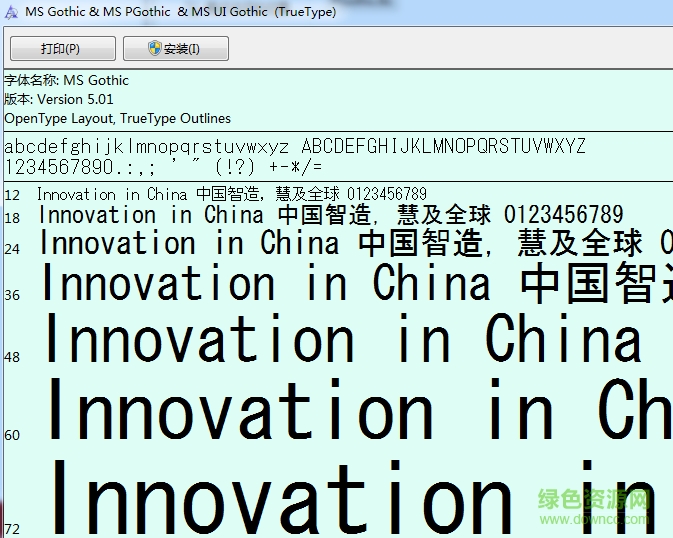
早就知道日文的字體,同樣的字體有帶P和不帶P的區(qū)別。比如"MS 明朝"和"MSP 明朝"。
但是一直不知道他們的區(qū)別,直到最近。
有P的是プロポーショナルフォント(Proportinal Font)-變幅字體
沒(méi)有P的是等(固定)幅フォント(Typewriter Font)-等幅字體
變幅字體字體幅度有大有小,自動(dòng)調(diào)整每行字的個(gè)數(shù)。
等幅字體字體固定大小,即使有標(biāo)點(diǎn)符號(hào)也不會(huì)改變每行字(標(biāo)點(diǎn)符號(hào))的個(gè)數(shù)。在文章中夾雜程序的時(shí)候,把程序的字體設(shè)成等幅字體,可以讓程序?qū)R,看起來(lái)更容易一些。